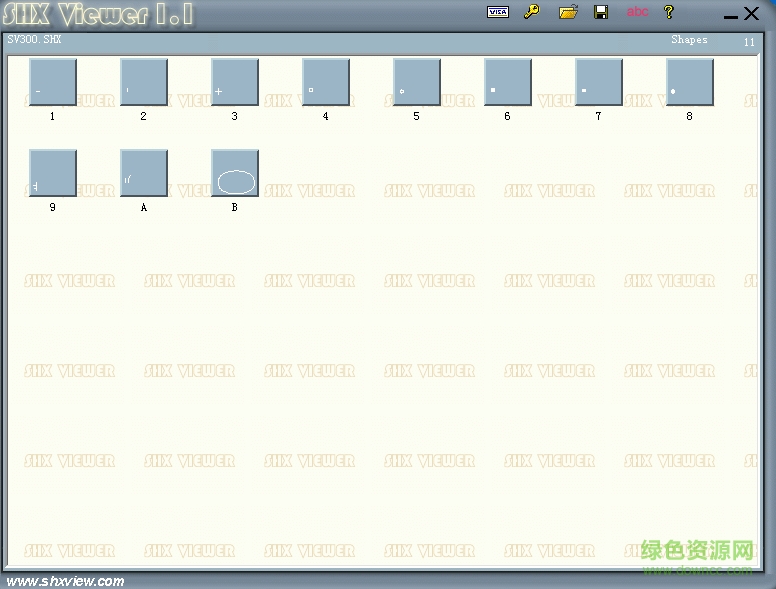
软件介绍 软件标签: sv300.shx shx字体 sv300.shx字体是一款漂亮的cad字体,字形干净优雅,使用效果良好,小编还为大家搜集了专门的cad字体安装器,一键批量安装,高效便捷,快来绿色资源网下载吧!sv300.shx字体安装方法1.下载并解压缩2.关闭正在运行的autocad软件3.将sv300.shx文件复制到AutoCAD安装目录下面的fonts目录下即可4.重新打开图形,即可正常显示cad字体安装器cad字体一键安装器可以帮助大家一键安装系统中没有的SHX格式字体。cad字体一键安装器 v1.0.0.0 绿色版授权:免费软件 WinAll大小:64.2M语言:中文cad字体一键安装器是一款能够快速的帮助用户安装shx格式字体的软件,系统字体不够丰富,那就赶快来下载该款软件快速的安装cad字体吧,方便快速,欢迎需要的朋友来绿色资源网下载体验吧!{insd m="2" i=&q下载地址 软件截图 上一张下一张(1 / 1) 安装详细截图 其他版本下载 标题 大小 更新日期 下载 gdt.shx,simplex.shx字体打包 AutoCAD最佳字体 11KB 2017-06-19 下载 1000SHP.SHX 1KB 2017-06-19 下载 runmap.shx字体 300KB 2017-06-19 下载 ssdi.shx 32KB 2017-06-19 下载 1000.shx 731KB 2017-06-19 下载 ktk.shx 937KB 2017-07-08 下载 下载地址 电脑版 sv300.shx字体 点击报错 软件无法下载或下载后无法使用,请点击报错,谢谢! 关闭报错反馈 请描述您所遇到的错误,我们将尽快予以修正,谢谢! *必填项,请输入内容 本类最新 dreamweaver字体库 首尔南山体字体 v1.06 官方版 潮字社风云简ttf 潮字社凌渡鲲鹏简体字体 潮字社曾玉波手书简字体 微博慧心字体 相关文章 我叫mt4哪个职业输出最高 我叫mt4输出最高的职业排行 将Access升级为SQL Server 2005 空白密码引发远程连接Server2008失败 Win2008终端服务器远程程序配置 用Windows 2003配置邮件服务器 windows 2003 服务器安全攻略 用户评论 热门评论 最新评论 发表评论 查看所有评论(0) 昵称: 请不要评论无意义或脏话,我们所有评论会有人工审核. 字数: 0/500 (您的评论需要经过审核才能显示)